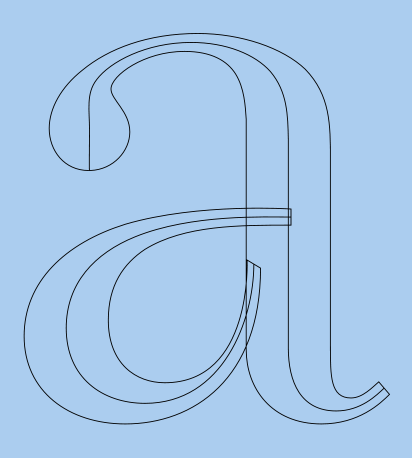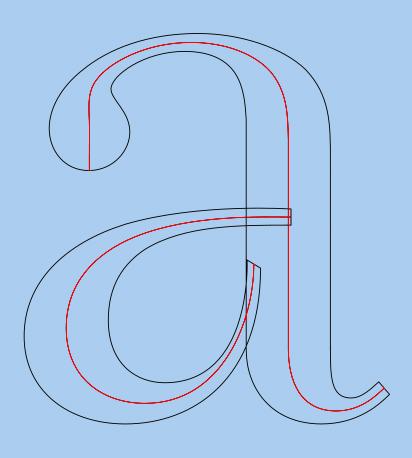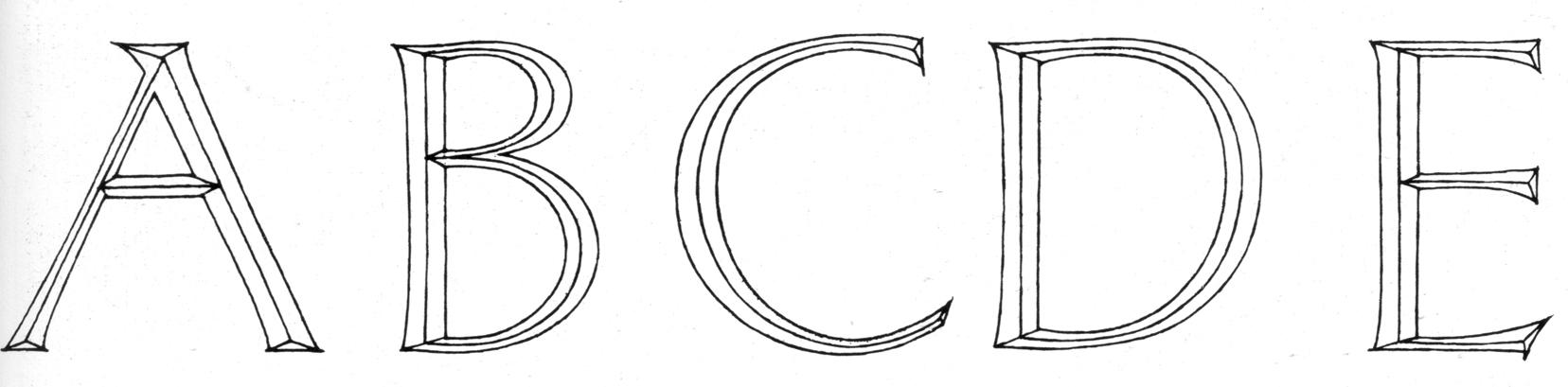
ich bin momentan am rätseln, was die korrekte typografische Übersetzung für den Begriff „center line“ ist.
Sagt man einfach Mittellinie oder Herzlinie? Vielleicht gibt es ja einen genauen Terminus in der Typografie.
Wenn damit nur eine gedachte Linie z. B. zur Konstruktion der Buchstaben gemeint ist, ist mir da der Ausdruck Skelett geläufig und in der Kalligrafie Gestus als Linie der Federführung.
Nein, Ich meine eigentlich die genaue Bezeichnung für die hier jetzt rot eingezeichnete Linie.
Belegt ist, dass Mittellinien bei Werkzeichnungen für den „Steinschnitt“ eingezeichnet wurden, um für den Steinmetz einen genauen Anhalt zu bieten.
Vielleicht könnte man die Bezeichnung „Schnittlinie“ hievon ableiten?
Anbei ein Ausschnitt einer Werkzeichnung für den Steinschnitt von Prof. Friedrich Neugebauer (1911–2005) aus dem Buch „Kalligrafie als Erlebnis“ v. Friedrich Neugebauer, 1979, Verlag Neugebauer Press, Salzburg.